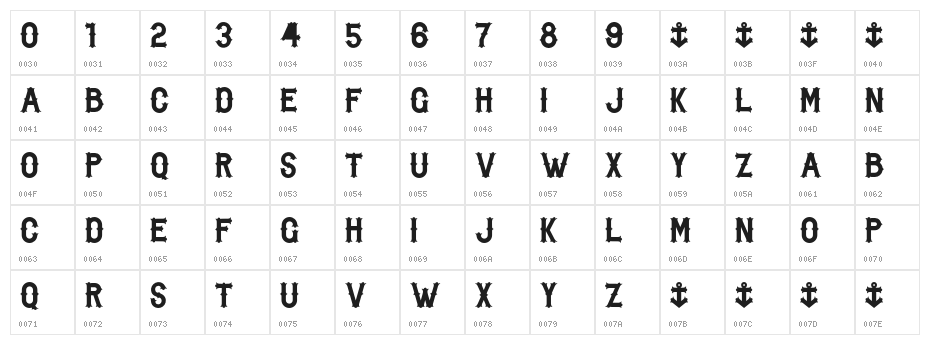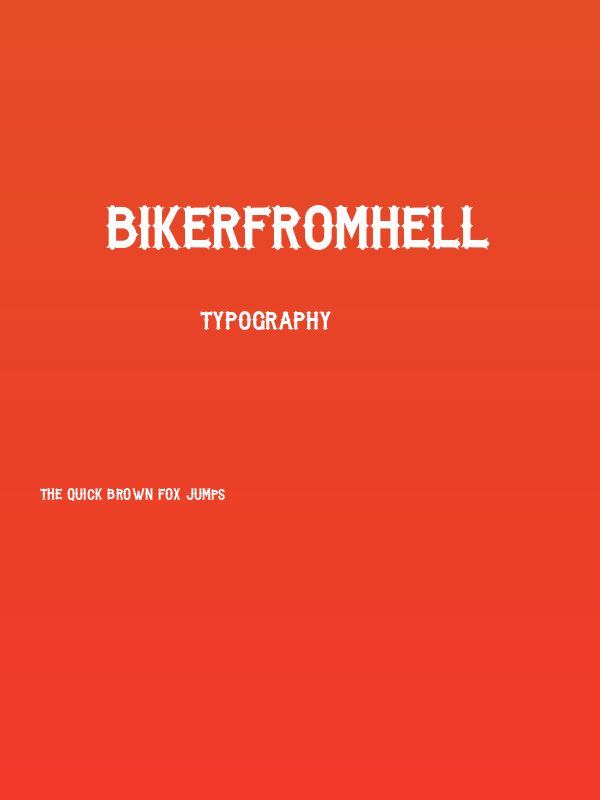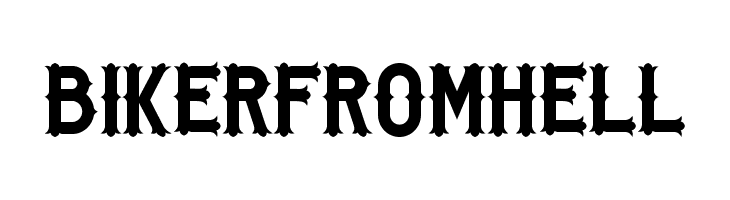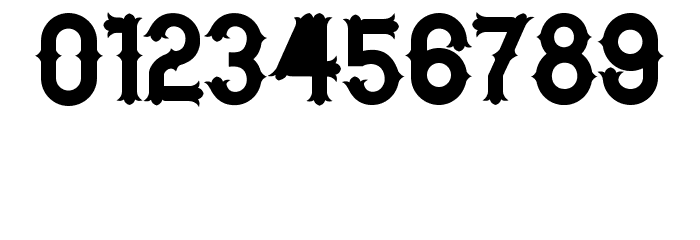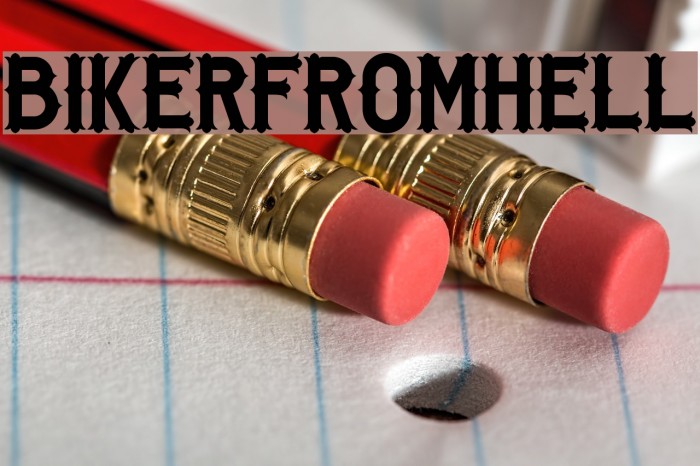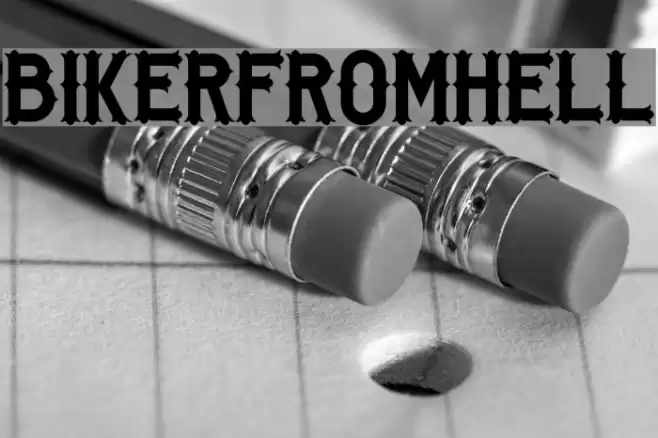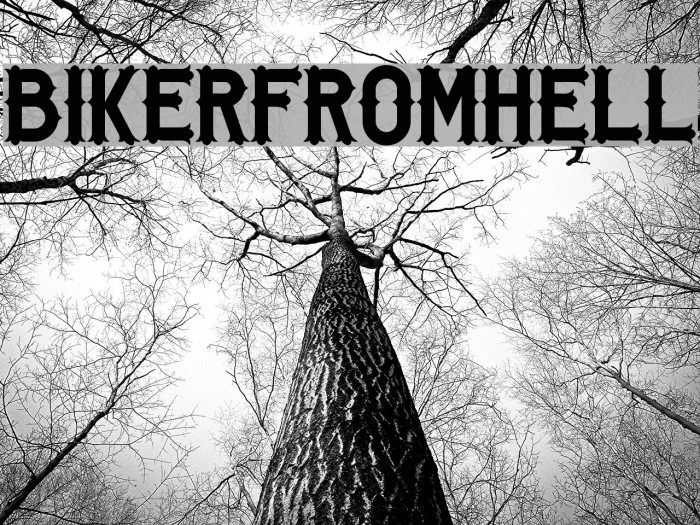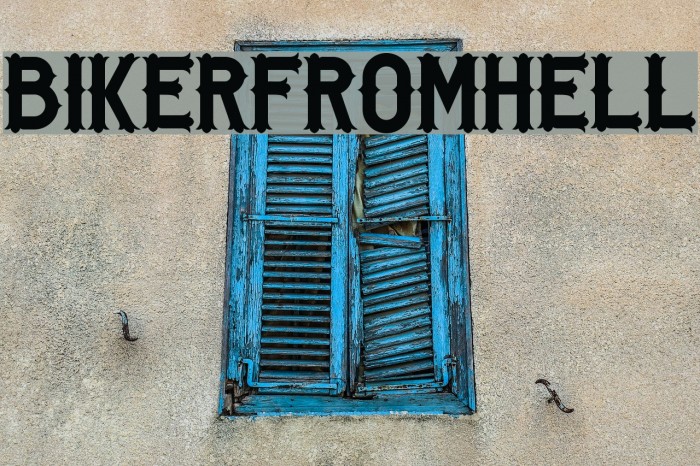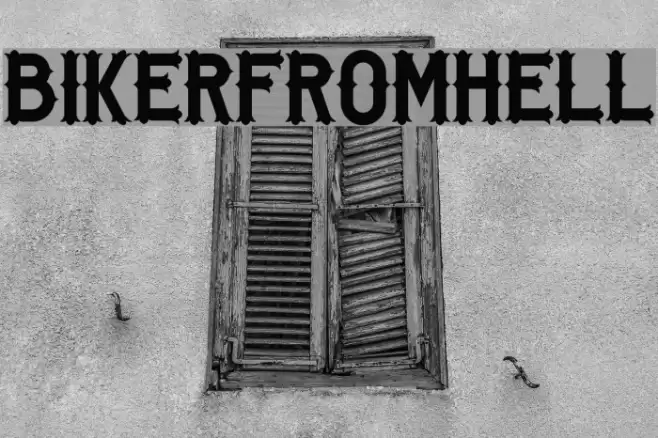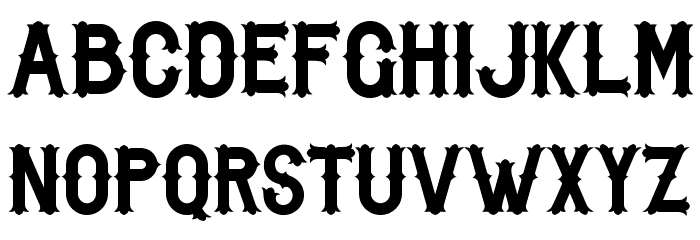
BikerfromHell Font
| कंट्रास्ट | High |
| समग्र शैली | Gothic, Edgy, Bold |
| उपयोग का मामला | Headlines, Logos, Posters |
| सुझाए गए प्रोजेक्ट | Ideal for branding, posters, album covers, and apparel designs that require a bold, edgy look. |